今回は、「埼玉県硬筆展に向けた練習の記録ギャラリー」シリーズの第3弾です!
今回も、子どもたちが清書まで取り組んだ作品をビフォーアフターでご紹介します。
左が練習を始めた頃に書いたもの、右が最後に清書した作品です。
清書用の紙(クリーム色)に変わると、気持ちも引き締まり、一文字一文字に集中して書いた様子が伝わってきます。
それでは、子どもたちの変化と成長の記録をご覧ください。
小学4年生
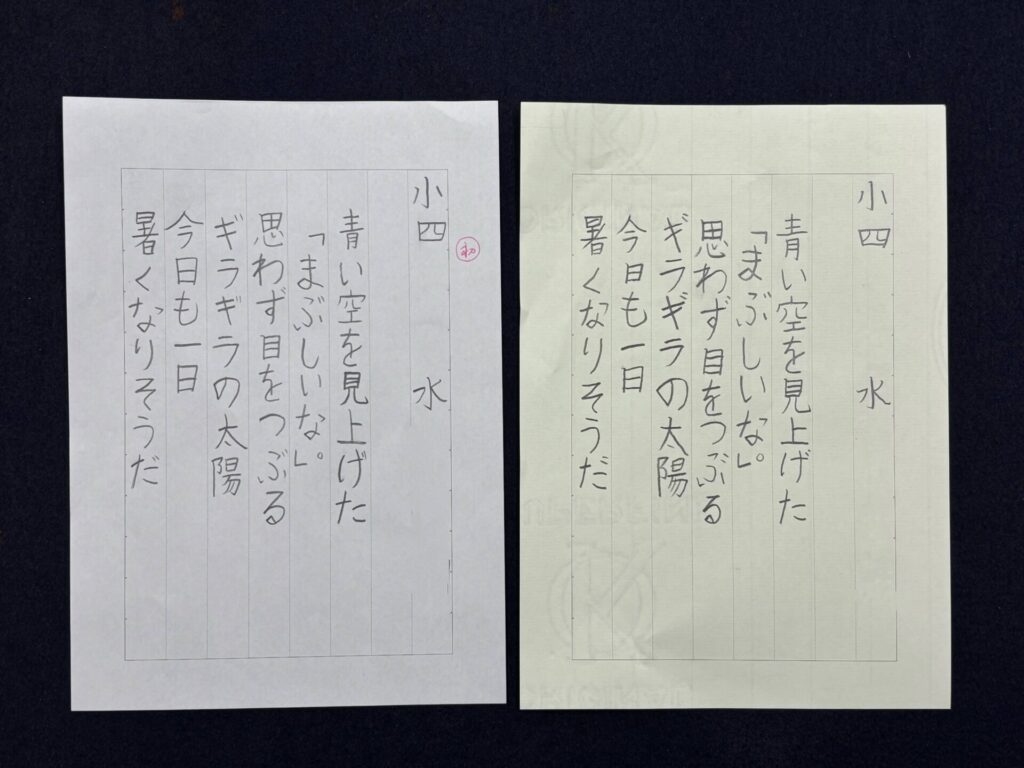
一文字ずつの形が安定し、全体がまとまって見えるようになりました。
特に「青い空を見上げた」の行は、縦のラインがしっかりそろって美しいです。
小学5年生
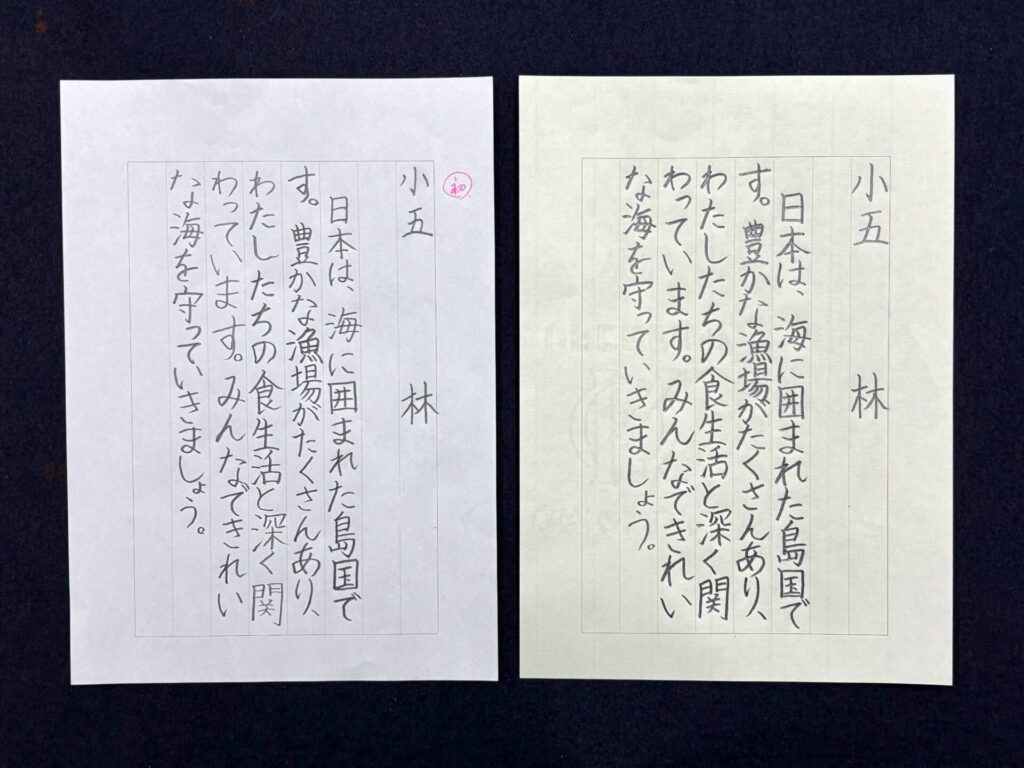
線の濃さと字の大きさに安定感が出て、読みやすい作品になりました。
最後まで落ち着いて書ききったことがよく伝わってきます。
小学5年生
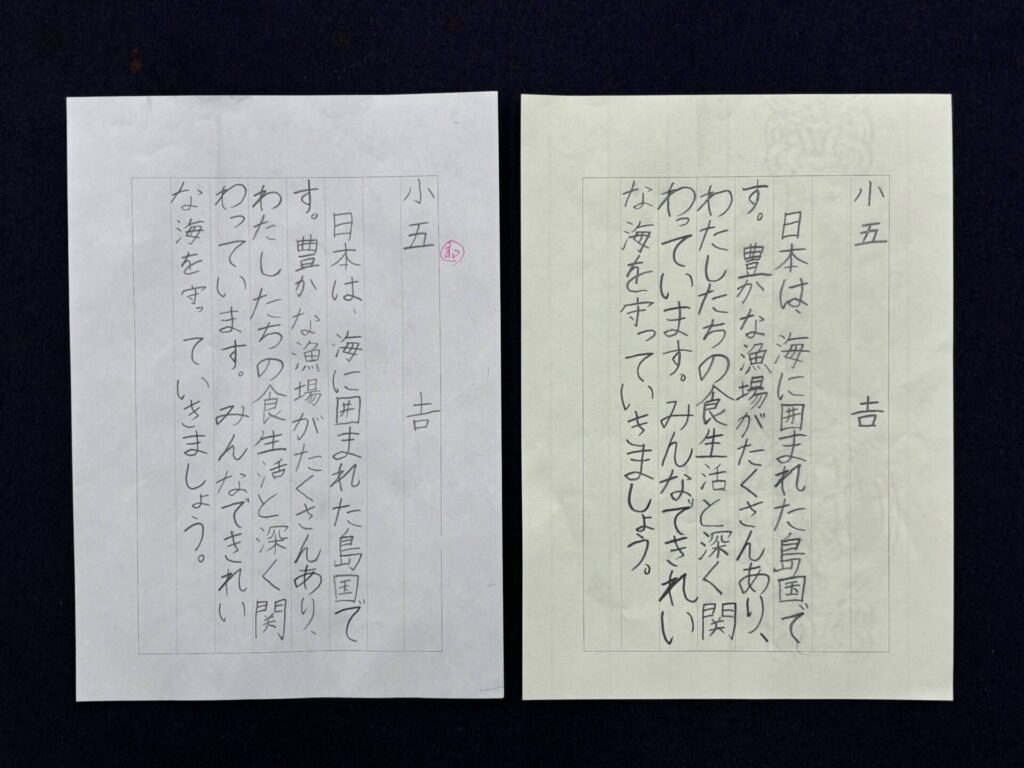
文字のバランスが整い、文の流れがなめらかに感じられるようになりました。
「漁場がたくさんあり、」の部分が、まとまっていて美しいです。
小学4年生
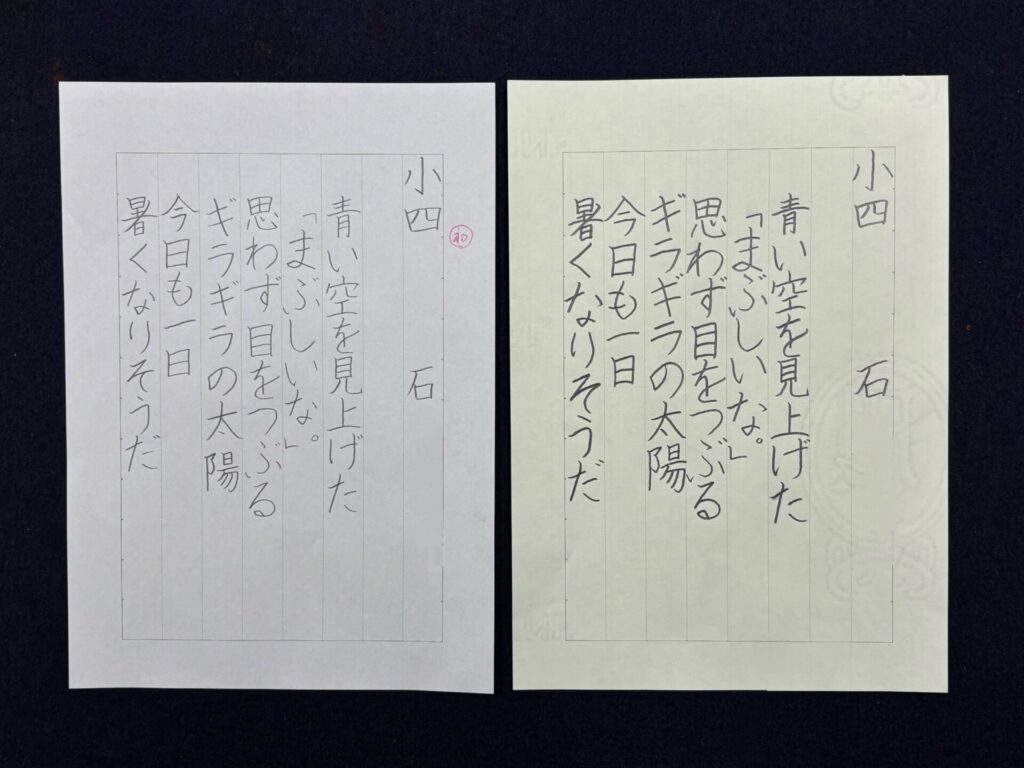
一画一画が濃くはっきり書けるようになり、のびのびとした印象になりました。
漢字の始筆がしっかりと美しく、ひらがなも素直でやわらかい線で書けています。
小学4年生
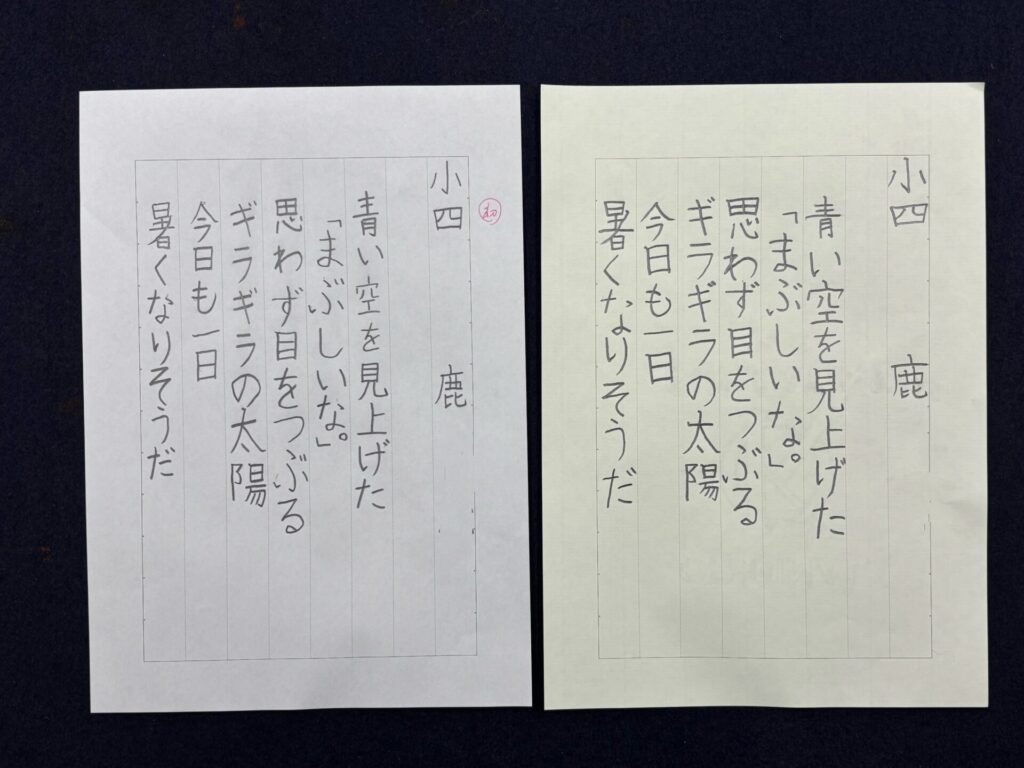
ひらがなと漢字の大きさのバランスが良くなり、全体が引き締まりました。
「今日も一日」がすっきり整って、気持ちのこもった清書になっています。
“書く”ことを通して気づく力と変化
毎回、こうして作品を並べてみると、目に見える変化だけでなく、
一文字一文字に、集中して取り組んだ様子が表れています。
どの子も、自分なりの「ここまでやりたい」という気持ちを持って清書に挑んでくれました。
うまくいかない日も、もう一度やってみようとした日も、すべてがこの1枚につながっています。
今回の作品も、そんな子どもたちの積み重ねが見えるものばかりです。